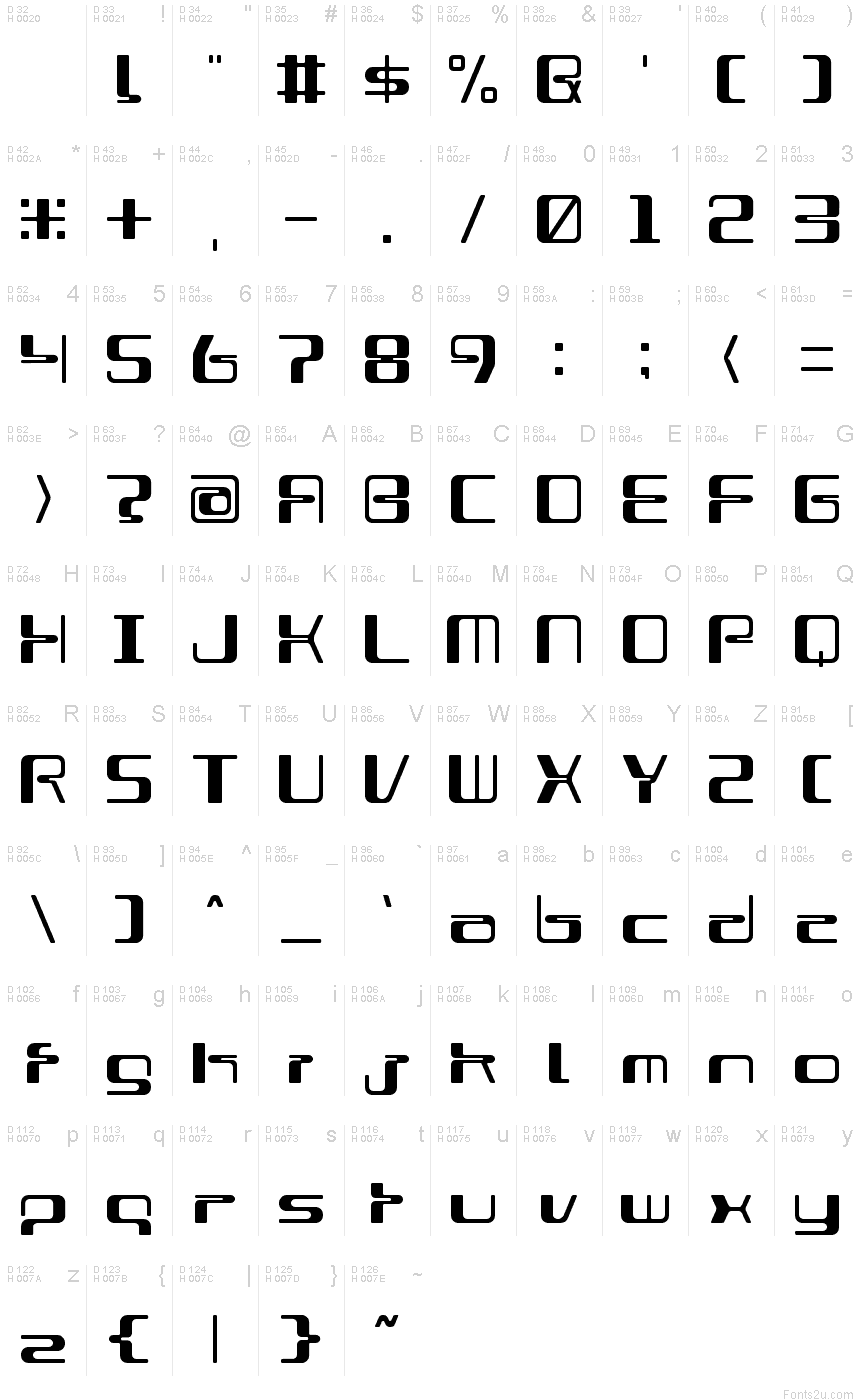
Clique di Kayo Masashi è un carattere display gratuito e groovy, con un'atmosfera mod morbida e un ritmo massiccio, quasi giocoso. Le maiuscole sembrano costruite con tratti ampi, angoli arrotondati e interni squadrati, conferendo alle lettere quell'aspetto accogliente dei poster anni '70, mentre la coda corta della Q mantiene l'insieme leggermente fuori dagli schemi.
È adatta per copertine di dischi, packaging di boutique, flyer di eventi, titoli e loghi brevi dove pochi caratteri possono reggere il look da soli. Essendo un font gratuito, si presta anche a fanzine, titoli di copertina e monogrammi, specialmente quando cerchi forme audaci e curve morbide invece di caratteri rigidi e formali.